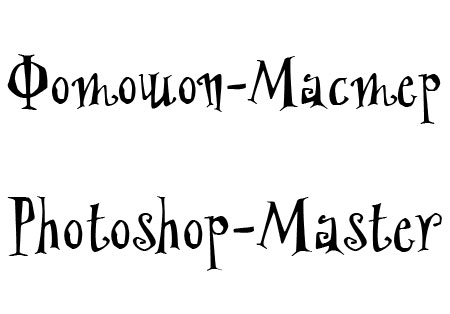
Дополнения Шрифты Татьяна Гапонова 7 августа 2009 Шрифт - PFWonderlandPro-Reg Необычный шрифт с поддержкой русского языка. Скачать Шрифт - PFWonderlandPro-Reg
Кошмар перед Рождеством? Интересно, надо качнуть.